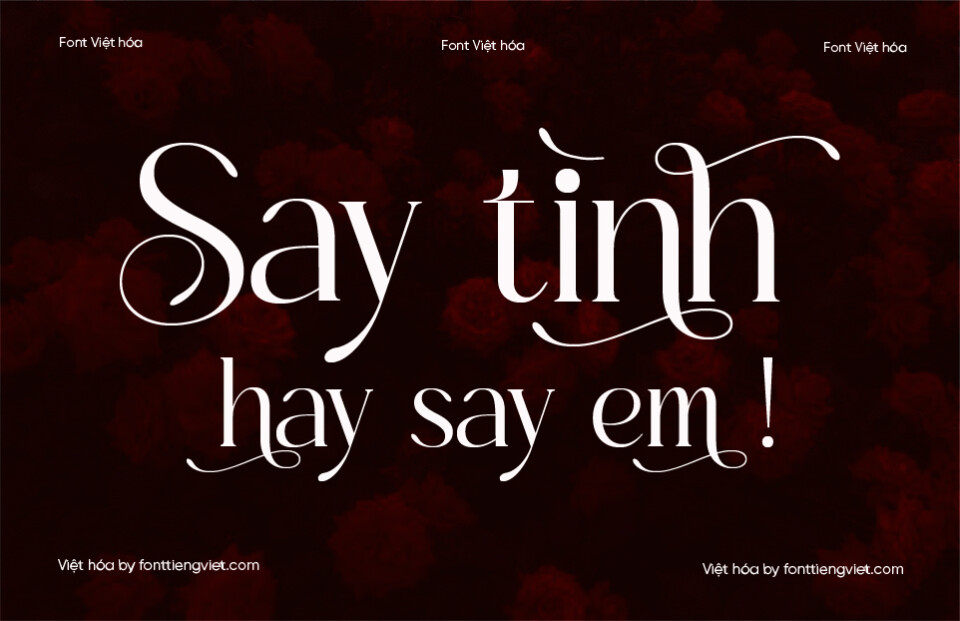
Font Việt hóa 1FTV VIP Foresta Monesta Serif – Font âm nhạc ca nhạc
Font Việt hóa 1FTV VIP Foresta Monesta Serif – Font âm nhạc ca nhạc đẳng cấp cho thiết kế sân khấu
Giới thiệu về Font Việt hóa 1FTV VIP Foresta Monesta Serif – Font âm nhạc ca nhạc
Trong thế giới thiết kế đồ họa hiện đại, việc lựa chọn một bộ Font Miễn Phí chất lượng đóng vai trò quyết định đến linh hồn của tác phẩm. Font Việt hóa 1FTV VIP Foresta Monesta Serif – Font âm nhạc ca nhạc là một siêu phẩm thiết kế mang phong cách Serif cổ điển nhưng không kém phần hiện đại. Bộ font này được đội ngũ 1FTV chăm chút kỹ lưỡng, tối ưu hóa từng đường nét để phục vụ riêng cho các chủ đề về nghệ thuật, âm nhạc và giải trí cao cấp. Với các đường chân chữ thanh mảnh và độ tương phản cao, Foresta Monesta mang đến cảm giác sang trọng, quý phái, rất phù hợp cho những ai đang tìm kiếm sự khác biệt trong tư duy hình ảnh.
Đặc điểm nổi bật của bộ font chữ này
Foresta Monesta Serif không chỉ đơn thuần là một bộ chữ cái mà còn là một công cụ truyền tải cảm xúc. Điểm nhấn lớn nhất chính là các ký tự thay thế (alternates) và các dấu nối (ligatures) đầy tính nghệ thuật. Khi sử dụng Font Việt hóa 1FTV VIP Foresta Monesta Serif – Font âm nhạc ca nhạc, bạn sẽ nhận thấy sự uyển chuyển trong cách sắp đặt bố cục, giúp tiêu đề trở nên bắt mắt và có chiều sâu hơn. Font đã được việt hóa hoàn chỉnh, loại bỏ hoàn toàn các lỗi hiển thị dấu tiếng Việt thường gặp, giúp các nhà thiết kế tại Việt Nam tự tin sáng tạo trên các phần mềm như Photoshop, Illustrator hay Canva mà không gặp bất kỳ trở ngại nào về mặt kỹ thuật.
Ứng dụng Font Việt hóa 1FTV VIP Foresta Monesta Serif – Font âm nhạc ca nhạc trong thực tế
Đúng như tên gọi, đây là lựa chọn số một cho các dự án liên quan đến ngành công nghiệp giải trí. Bạn có thể sử dụng bộ font này để thiết kế bìa album nhạc, poster liveshow ca nhạc hoặc backdrop cho các sự kiện văn nghệ tại nhà trường. Vẻ đẹp của Font Việt hóa 1FTV VIP Foresta Monesta Serif – Font âm nhạc ca nhạc giúp tôn vinh tên tuổi người nghệ sĩ và làm nổi bật thông điệp nghệ thuật. Bên cạnh đó, các nhãn hàng thời trang hay mỹ phẩm cũng rất ưa chuộng phong cách Serif này để tạo dựng hình ảnh thương hiệu đẳng cấp và tin cậy trong mắt khách hàng.
Lý do nhà thiết kế nên sở hữu bộ font này
Sở hữu một bộ font “VIP” giúp bạn tiết kiệm thời gian chỉnh sửa thủ công các dấu tiếng Việt rời rạc. Foresta Monesta Serif được thiết kế với độ cao ký tự chuẩn, khoảng cách giữa các chữ cái (kerning) được tinh chỉnh hợp lý để đảm bảo tính dễ đọc ngay cả ở kích thước nhỏ. Đặc biệt, phong cách âm nhạc ca nhạc của font giúp gợi liên tưởng đến những bản nhạc thính phòng hay những buổi biểu diễn jazz đầy cảm hứng. Việc kết hợp font này với các tông màu vàng gold, đen huyền bí hoặc đỏ đô sẽ tạo nên những sản phẩm đồ họa có sức hút mạnh mẽ, chuyên nghiệp và đầy tính thẩm mỹ.
Cách sử dụng và kết luận về Font Việt hóa 1FTV VIP Foresta Monesta Serif – Font âm nhạc ca nhạc
Để phát huy tối đa vẻ đẹp của bộ font, bạn nên sử dụng chúng cho các tiêu đề lớn hoặc các câu trích dẫn ngắn gọn. Tránh dùng cho các đoạn văn bản quá dài để không gây mỏi mắt cho người xem. Tóm lại, Font Việt hóa 1FTV VIP Foresta Monesta Serif – Font âm nhạc ca nhạc là một tài nguyên quý giá cho cộng đồng sáng tạo. Nếu bạn đang tìm kiếm các mẫu Font Miễn Phí, Font Việt Hóa, Font Việt hóa 1FTV VIP Foresta Monesta Serif – Font âm nhạc ca nhạc thì đây chắc chắn là cái tên không thể bỏ qua trong bộ sưu tập cá nhân. Hãy tải ngay để trải nghiệm sự tinh tế và đẳng cấp trong từng nét chữ mà bộ font này mang lại cho dự án của bạn.